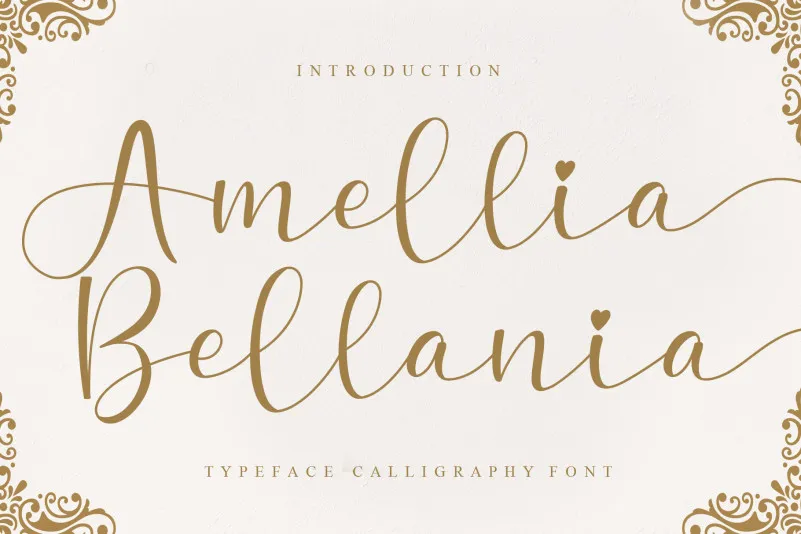
A fonte ‘Amellia Bellania Calligraphy Font’ é uma criação criativa que oferece aos designers a oportunidade de experimentar algo único no mundo do design tipográfico. Especialmente projetada para quem busca um estilo elegante e sofisticado, esta fonte vem com nuances sutis e detalhes meticulosamente elaborados, capaz de dar vida a qualquer projeto que ela toca. Com seu script fluido e elegante, ‘Amellia Bellania Calligraphy Font’ torna-se uma escolha popular para designers que procuram um toque de glamour em suas criações. Perfeita para textos legíveis mas com o charme único das fontes calligráficas, essa fonte irá marcar seu projeto e destacar a sua personalidade criativa. Para os amantes do design que desejam incorporar um ar sofisticado e autêntico em seus projetos, esta ‘Amellia Bellania Calligraphy Font’ é uma opção ideal. Através de sua graça fluida e detalhes cuidadosamente definidos, a fonte se tornará um dos principais aliados do seu trabalho de design.